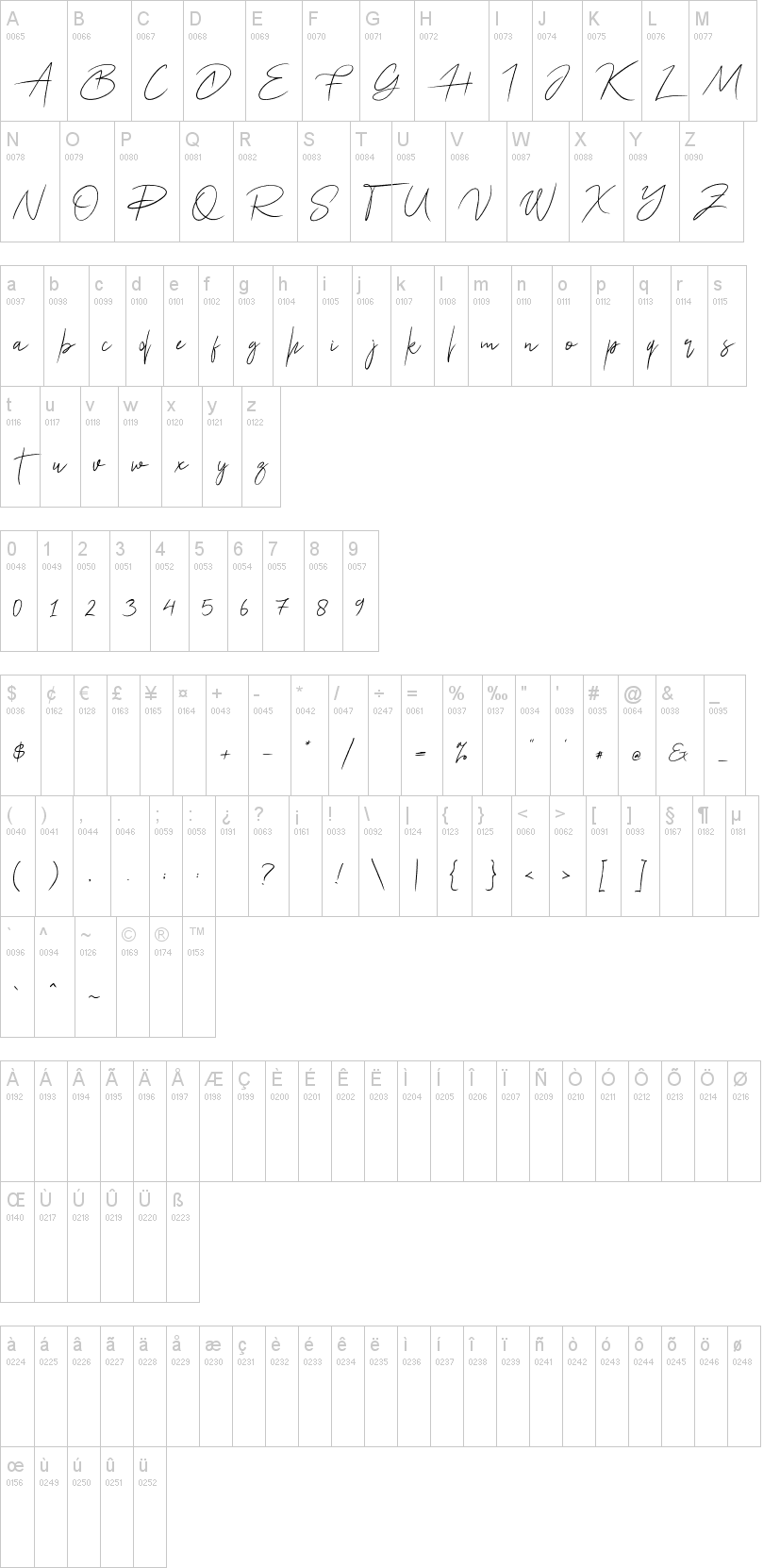
Ariel Script
Ariel Script 是一款由 Monotype 公司设计的西文字体,它是一种草书字体,具有优雅、精致、流畅的笔画,带有细腻的线条,给人一种温柔、柔美的视觉感受。它的字形特点是比较宽松,曲线流畅,笔画柔和,字形结构精致,比较容易识别,使用起来较为方便。它适用于广告、标识、杂志、书籍等各种设计领域,可以提升作品的视觉效果,使文字更加清晰、美观。
Ariel Script是一款非常不错的手写艺术字体,具有很好的视觉感,适合于文化类的宣传设计、商业类品牌的广告和产品包装设计以及个性化文字排版等较多场景。
Ariel Script字符映射图